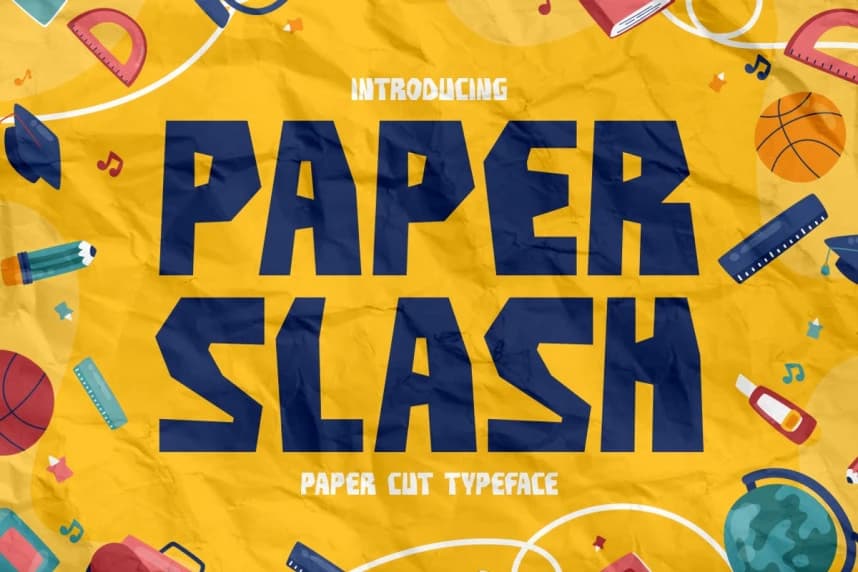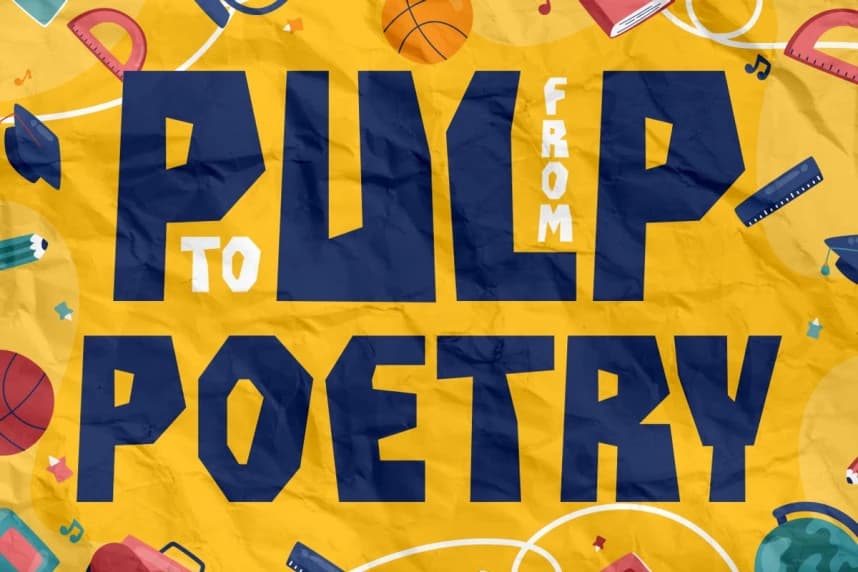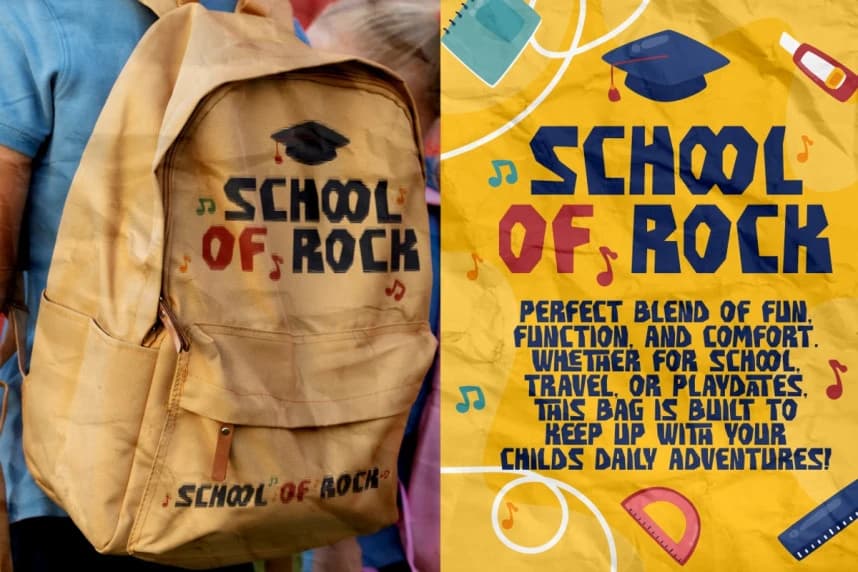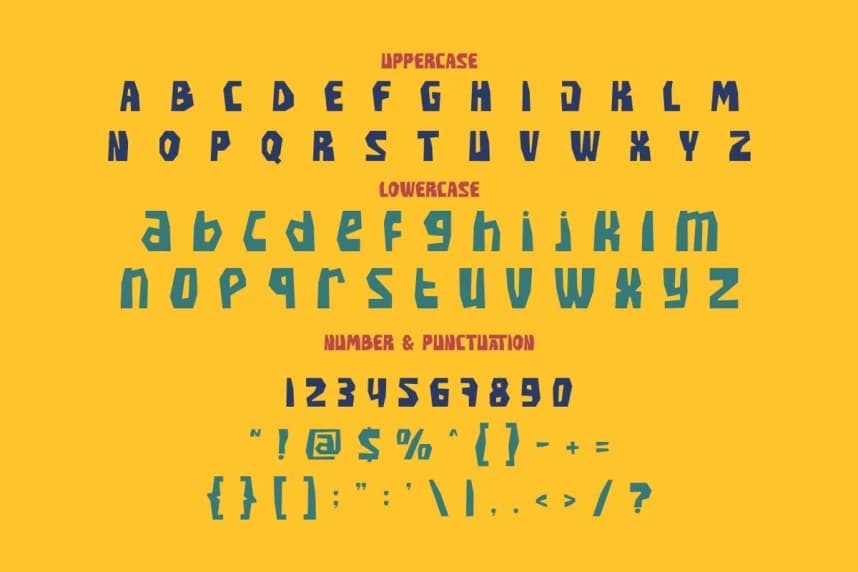
Paper Slash Font
Paper Slash Font - Paper Cut Typeface, tasarımlarınıza kesilmiş kağıt harflerin çekiciliğini getiren eğlenceli, cesur ve benzersiz bir el yapımı font. Bu eğlenceli gösterim yazı tipinin keskin ve düzensiz kenarları, el kesimi kağıt şekillerini taklit eder ve tasarımlarınıza dinamik ve enerjik bir hi
Paper Slash Font - Paper Cut Typeface, eğlenceli, cesur ve özgün biçimde el yapımı bir font olup tasarımlarınıza kesilmiş kağıt harflerin çekiciliğini getirir. Bu neşeli gösterim yazı tipi, elle kesilmiş kağıt şekillerini taklit eden keskin, düzensiz kenarlara sahiptir ve dinamik ve enerjik bir his yaratır.